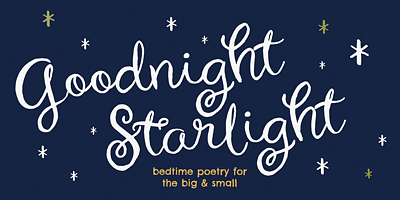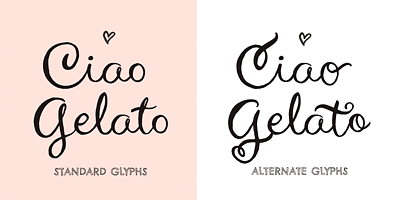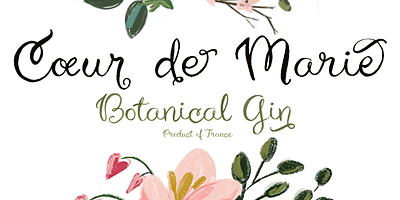
Chelsea Market Script est une police cursive peinte à la main avec des ligatures douces et de délicieux caractères alternatifs. Elle est parfaite pour les logos, les titres et les articles cadeaux.